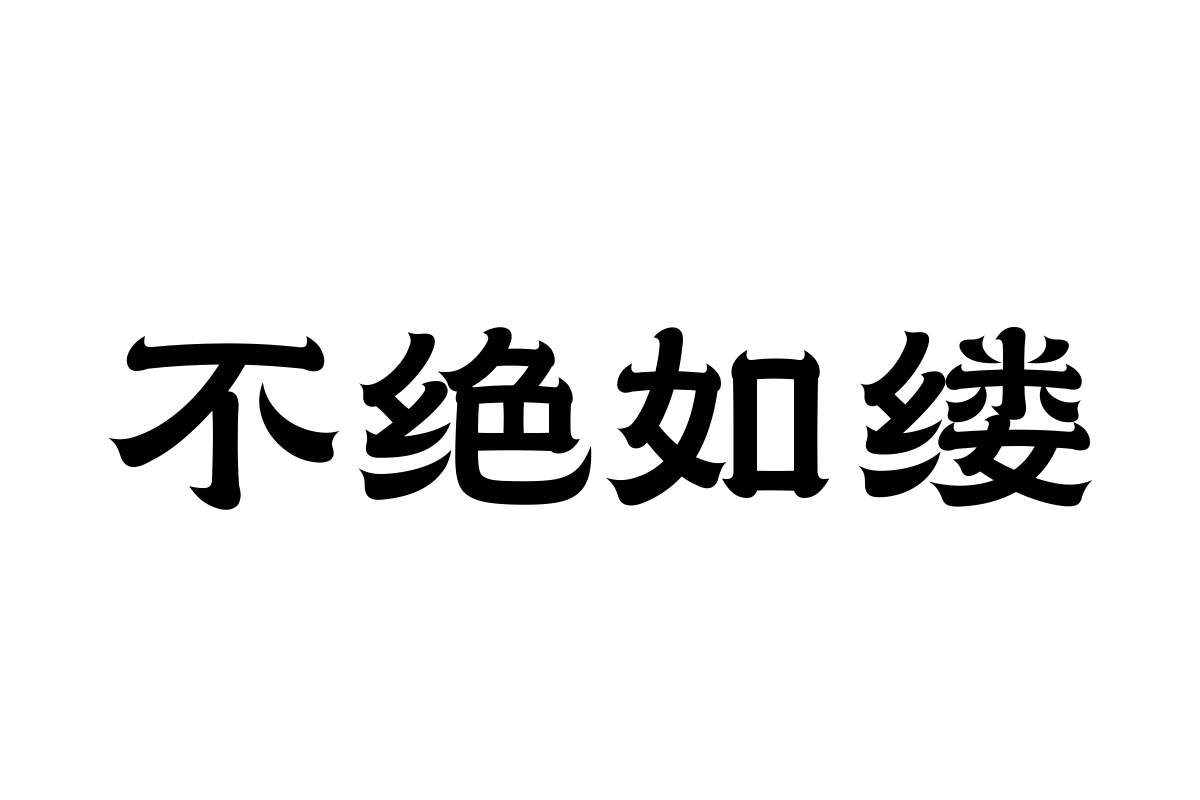
汉仪赤云隶 75W 是一款具有现代感的中文字体,它由汉仪字库公司设计。这款字体的特点是笔画流畅,结构紧凑,适合用于各种需要强调文字美感和清晰度的场景。它的设计风格独特,既有传统书法的韵味,又不失现代简洁的特点。无论是用于广告设计、网站界面还是其他需要展示文字美感的场合,汉仪赤云隶 75W 都能展现出其独特的魅力。